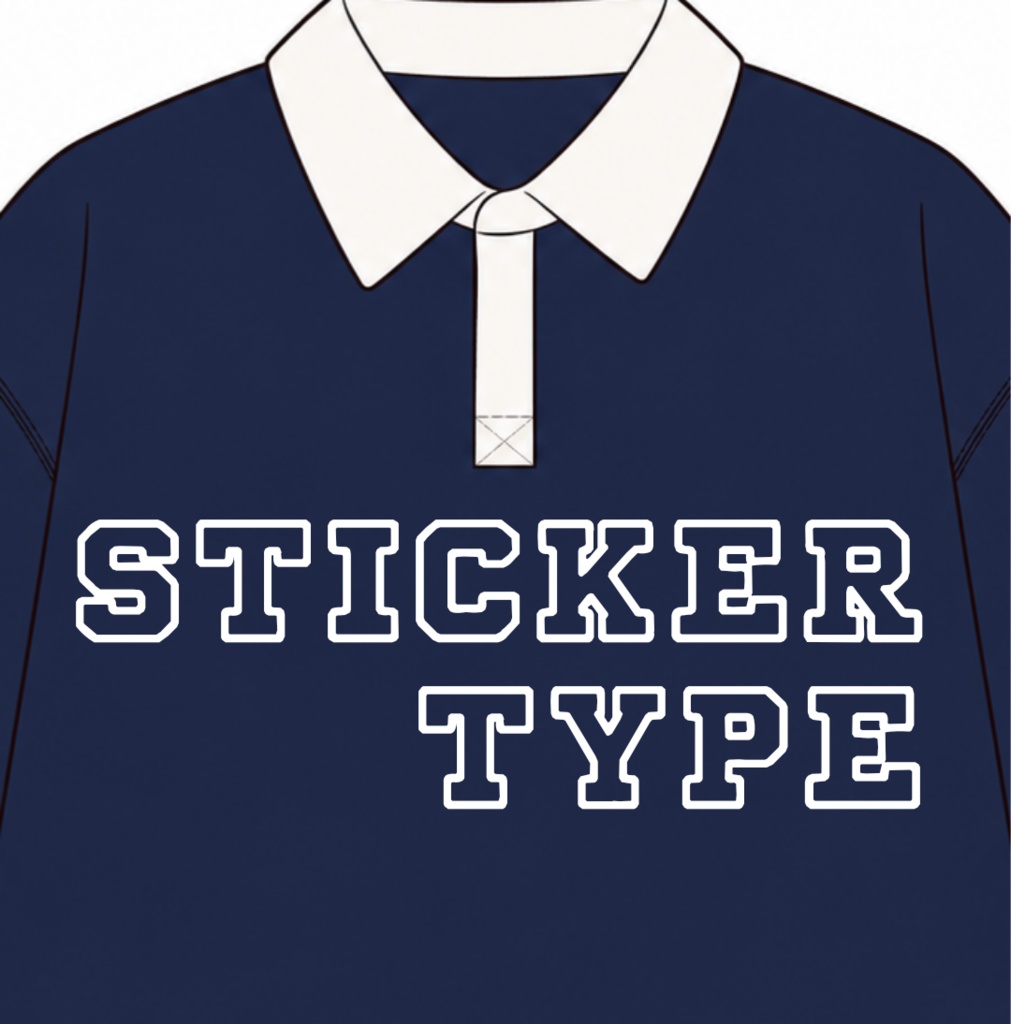
kireikirei欧文フリーフォント_STICKER TYPEダウンロード商品¥ 0無料ダウンロードSTICKERTYPE.zip (9.17 KB)STICKERTYPE.zip「ギフトとして贈る」とは太めアウトラインが特徴の欧文フォント「STICKER TYPE」です 利用規約は下段に書いておりますので、ご一読の上ご使用ください 収録文字 アルファベット大文字と数字のみ ABCDEFGHIJKLMNOPQRSTUVWXYZ0123456789 直接otfを置けないため、zipにしています利用規約対応文字:大文字(A-Z)・数字(0-9)のみ(小文字・約物・日本語には対応していません) カーニング調整なし AIを制作の一助として使用し、一部デザインを手作業で調整しています 商用利用:OK ゲームでの使用:OK フォントファイル自体の販売・再配布:不可 「自作フォント」としての公表:不可kireikireiFANBOX開設中イラスト素材立ち絵_黒髪ゴスロリ少女kireikirei¥ 300イラスト素材【Vtuver素材】ギンガムチェックエプロンワンピース衣装 2色セット / Gingham Check Pinafore Dress Costume Set (2 Colors)kireikirei¥ 300素材(その他)【VTuber素材】グッドハンドアセット(手のみPNG)kireikirei¥ 200素材(その他)お着替えセーラードレス素材(紺/白2色)kireikirei¥ 300イラスト素材🌹赤薔薇ゴスロリドレス 衣装差分素材【黒・白2色セット】kireikirei¥ 300イラスト作品女の子1_茶髪ゆるふわ女子立ち絵_表情差分ありkireikirei¥ 300もっと見る